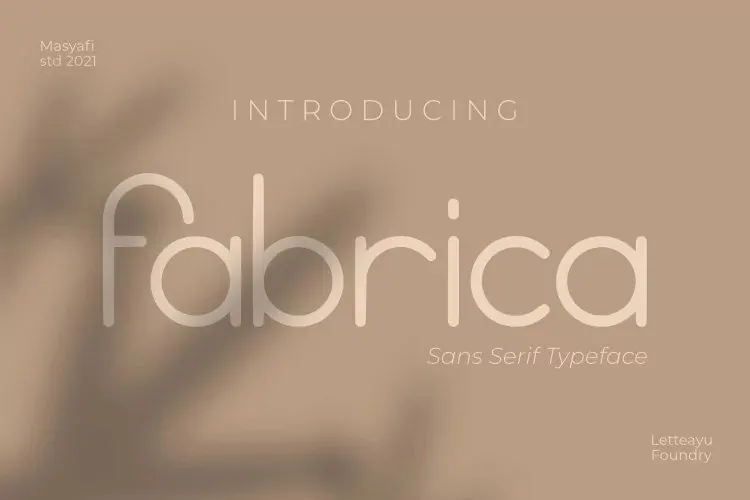
A “Fabrica Font” é uma elegante fatura sans-serif inspirada nas práticas de escrita de estudantes. Seus trabalhos limpos e minimalistas são perfeitos para logotipos, headlines, posters, embalagens e muito mais! Com três diferentes pesos disponíveis, as possibilidades para criar designs únicos e versáteis se expandem ainda mais. Experimente a “Fabrica Font” e inspire-se com uma variedade de novas ideias gráficas em seu próximo projeto.